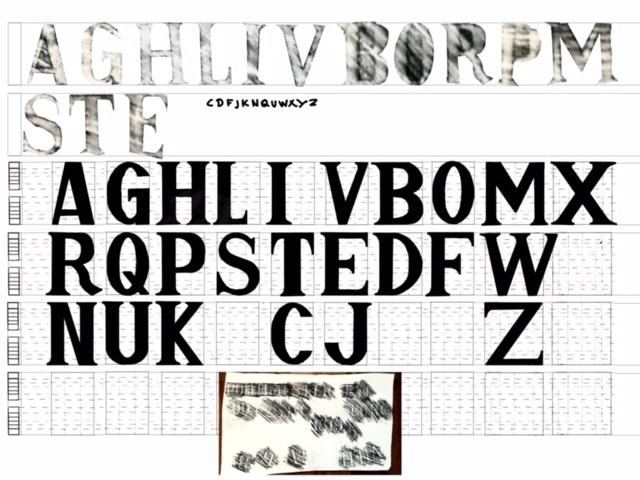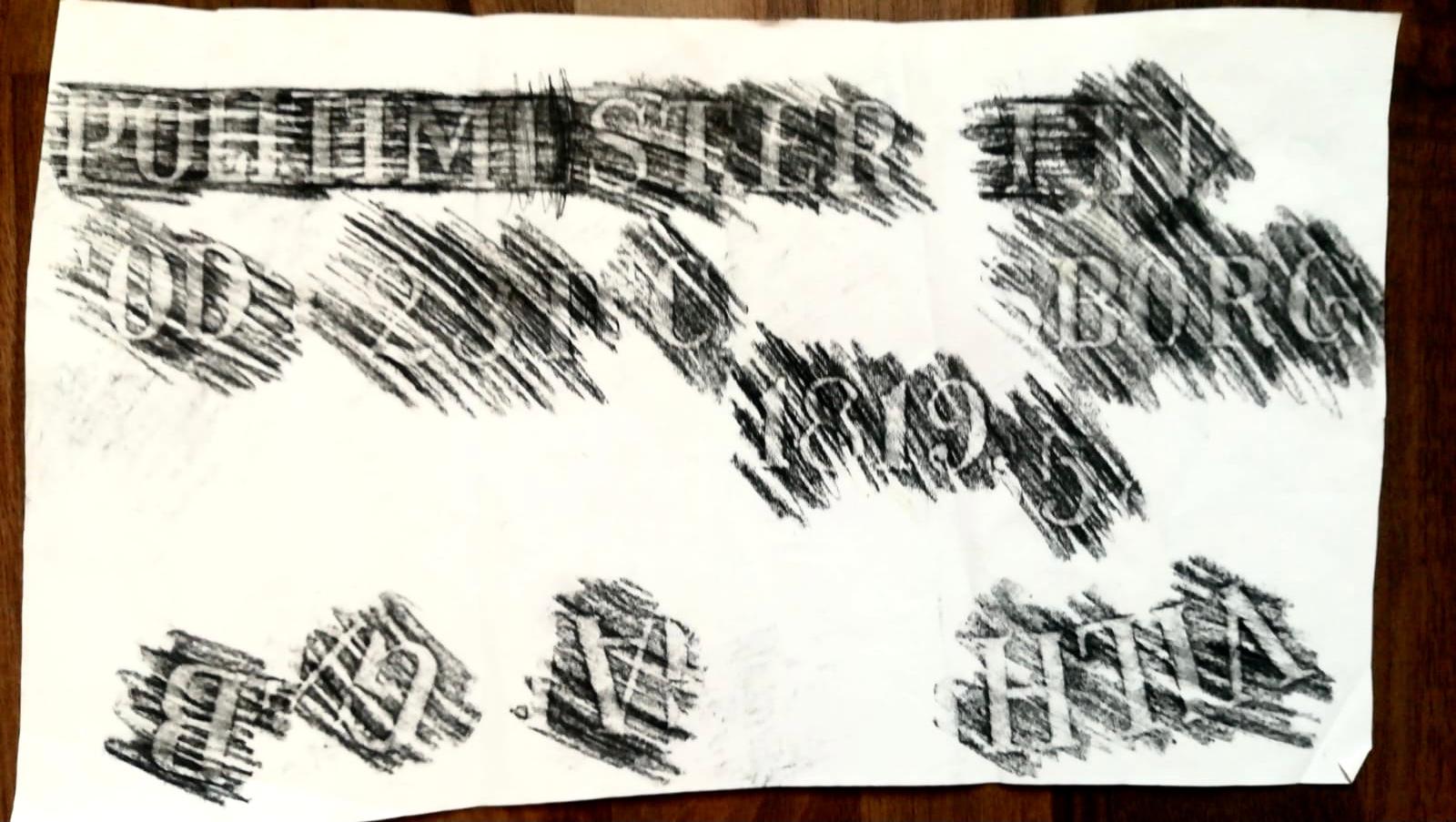
Identifikation und Vervollständigung einer Schrift vom Friedhof
im Rahmen meiner Ausbildung zum Holzbildhauer versuche ich derzeit über ein Foto von einer Frottage - zugegeben eine schlechte Referenz - das Alphabet der Majuskeln sowie die Zahlen einer Schrift vom Friedhof zu komplettieren. Den einzigen Hinweis auf eine zeitliche Einordnung zur Identifikation der Schrift bietet dabei die Jahreszahl 1819.
Erkennt jemand die Schrift und könnte mir den Namen verraten, wäre ich deshalb überaus dankbar!
Meine bisherige Arbeit - genauer das vermutete Raster - scheint mir nämlich fehlerhaft zu sein, was angesichts meiner wenigen Anhaltspunkte durch das Foto wenig verwunderlich ist.
Auch Tipps und Tricks zur Rekonstruktion helfen mir ungemein!
Epigraphische Schriften abzureiben und sich damit zu beschäftigen ist eine interessante Sache (Friedhofsschriften überhaupt). Aber woher „die Vermutung eines Rasters“ hier kommt ist mir absolut schleierhaft. Von solchem Hokuspokus bitte unbedingt die Finger lassen (die oben gezeigte Skizze demonstriert brachial den Holzweg). Stattdessen empfehle ich mit Nachdruck, sich die typographischen Schriften aus der Zeit genau anzusehen und sie mit den epigraphischen zu vergleichen.
Wobei es aber eben doch nicht auszuschließen ist, dass Steinmetze für den Entwurf ihrer spezifischen Schrift auch Hilfsraster-Konstruktionen verwendet haben. In den Lehrbüchern für Steinmetze, Schildermaler oder andere in der Zeit mit Shrift arbeitende Handwerke sind solche Konstruktionswege ja gezeigt. Das dann aber aus der damm oft verfeinerten tatsächlich umgesetzten Schrift zurück zu schließen,ist dann doch eher ein Kartenlesen.